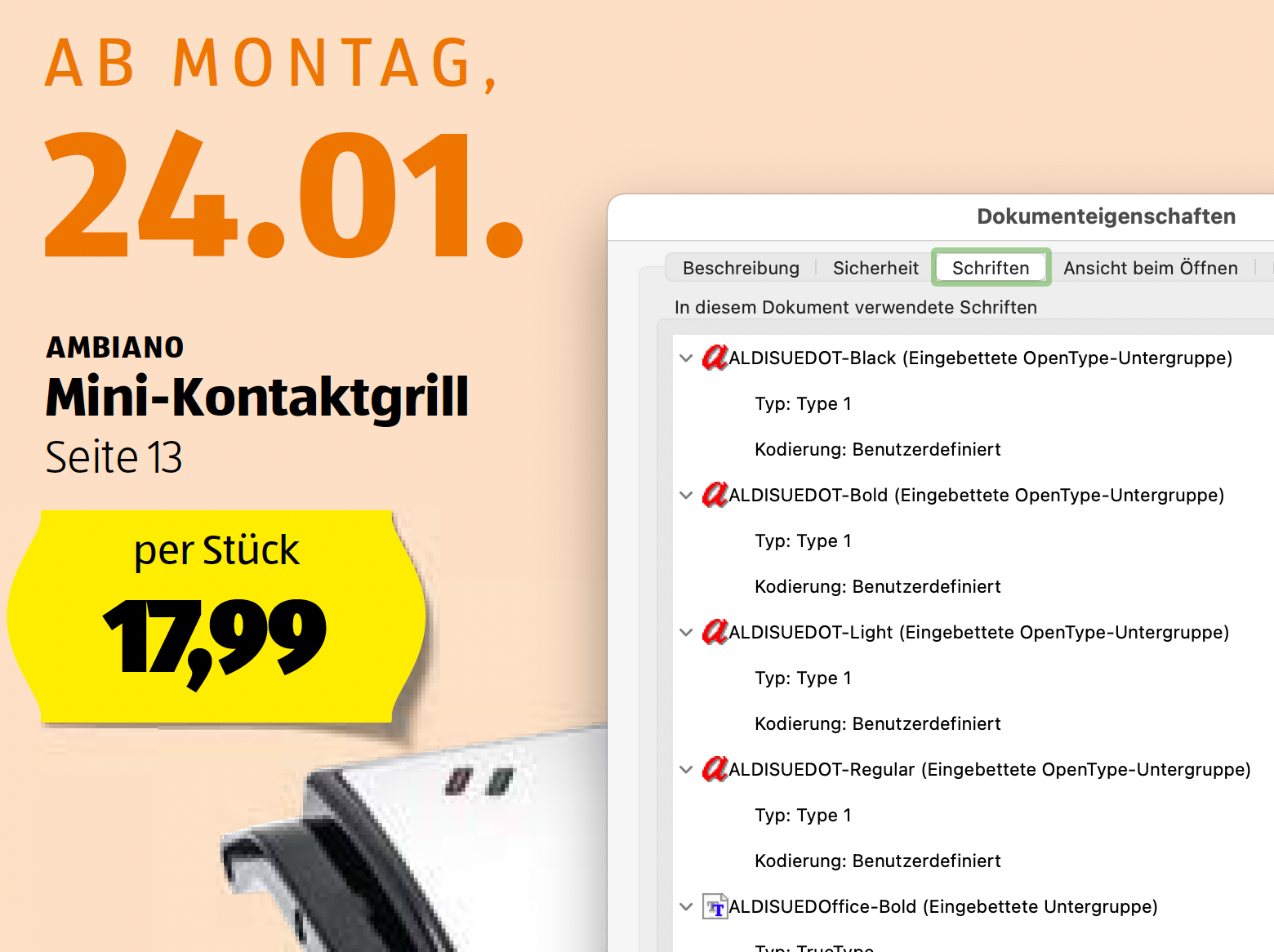
Aldi SÜD Font gesucht!
Ich suche den Font von Aldi SÜD. Für einen kleinen Tipp wäre ich dankbar!
Also das ist nicht exakt die Syntax. Der Aldi-Konzern hat sich (wohl) für das neue Logo eigens eine Variante erstellt und lizensieren lassen (besonders ersichtlich im Hofer-Logo beim F). Bei welcher Foundry weiß ich nicht, aber auf jeden Fall ist es nicht die Syntax LT.
Hallo @roti8, der Original-Post ist von 2005. Damals traf die Schriftidentifikation sicherlich zu. In den seitdem vergangenen 17 Jahren wurde das Corporate Design von Aldi Süd aber geändert. Die aktuelle Exklusivschrift stammt aus dem Hause FontShop und ist bereits seit (spätestens) 2013 in Gebrauch – auch bei Hofer.